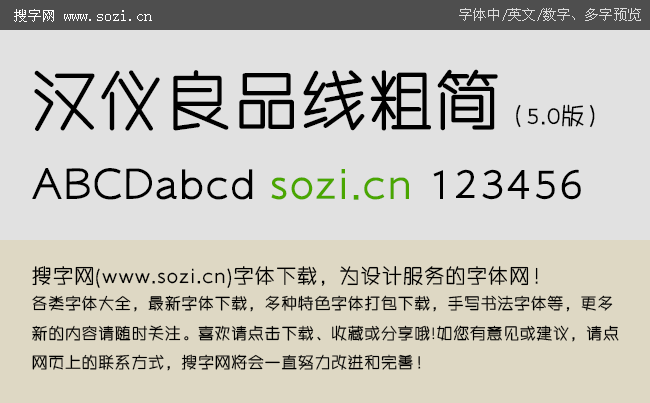
漢儀良品線粗簡(jiǎn)
搜字網(wǎng)提供一款漢儀良品線粗體簡(jiǎn)體藝術(shù)字體下載。這款字體清新規(guī)整,充滿(mǎn)簡(jiǎn)約的設(shè)計(jì)感,重心偏低穩(wěn)定性高,筆畫(huà)由直線組成,線條簡(jiǎn)單靈動(dòng),使人感覺(jué)優(yōu)雅有品質(zhì)。在圓體的基礎(chǔ)上加入大膽的改變調(diào)整,使得整套字更有現(xiàn)代感。適合畫(huà)冊(cè)標(biāo)題、海報(bào)設(shè)計(jì)、廣告宣傳等場(chǎng)合使用。